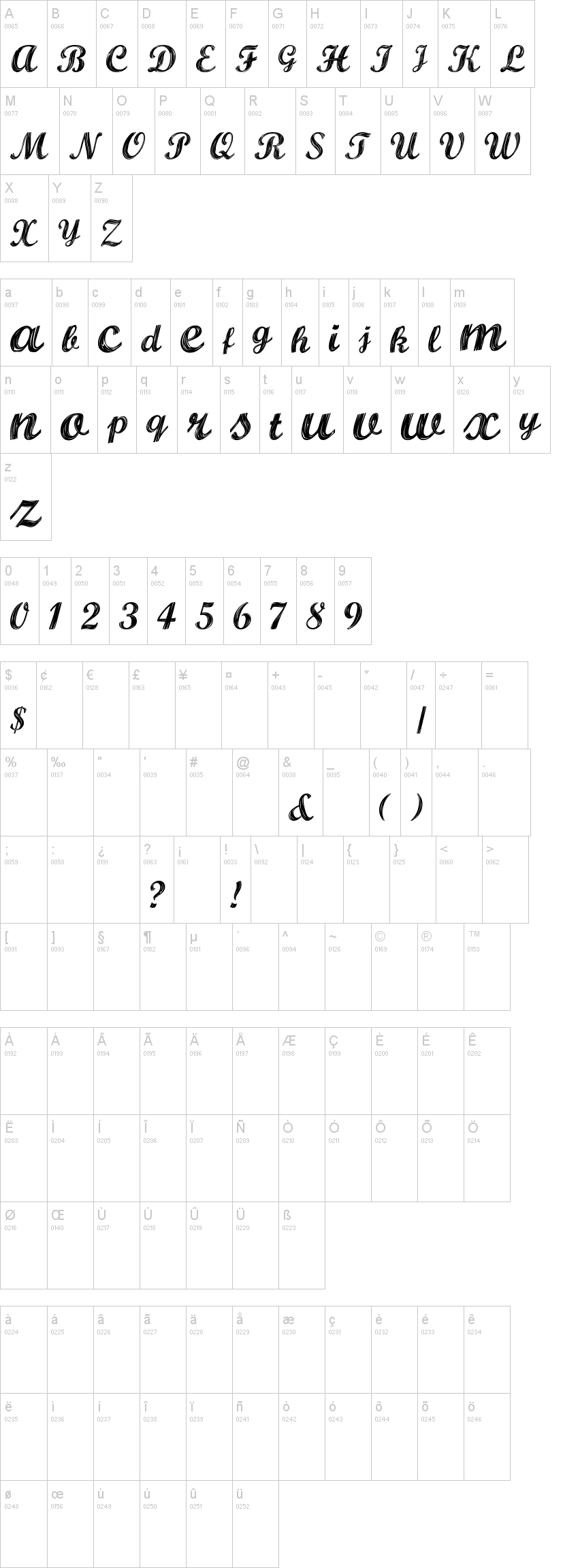
Albura
Albura 字体是一种拉丁文字体,由葡萄牙设计师 Ricardo Santos 设计。它的特点是每个字母都有自己独特的细节,给人以温暖感,更具有节奏感。它的风格融合了拉丁文字体和现代字体的特征,具有轻松、简洁、优雅的外观,可以用于排版、平面设计、海报、标志、标识等多种应用场景。
Albura是一款非常不错的手写艺术字体,具有很好的视觉感,适合于文化类的宣传设计、商业类品牌的广告和产品包装设计以及个性化文字排版等较多场景。